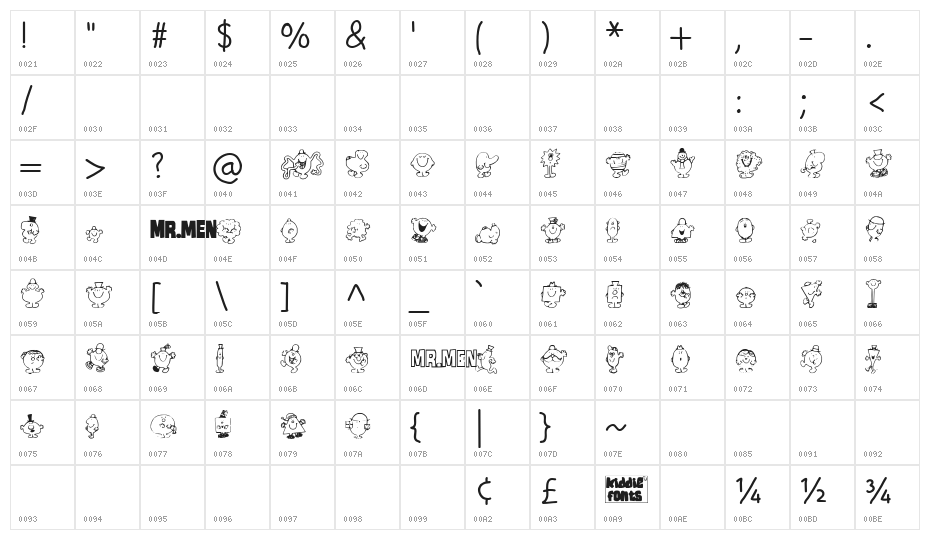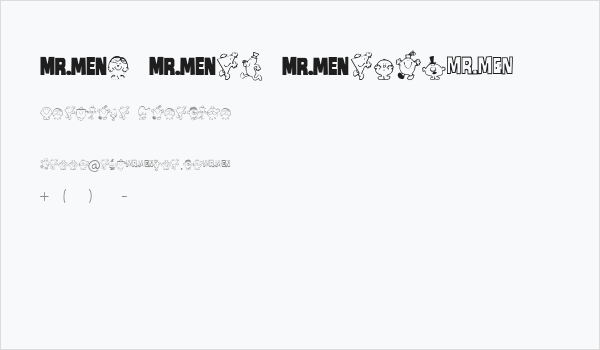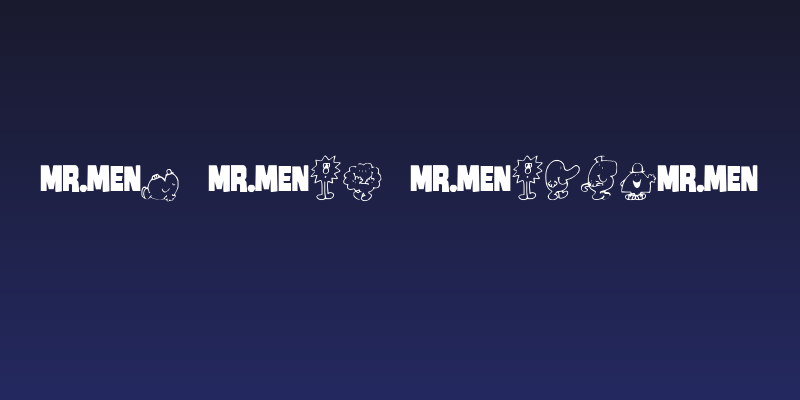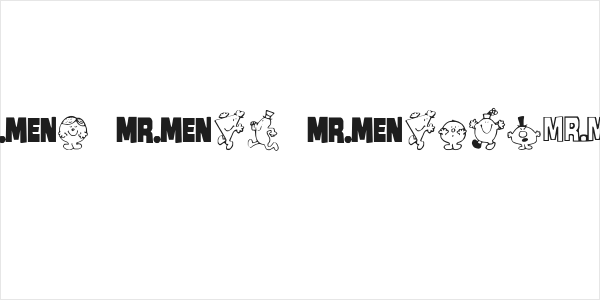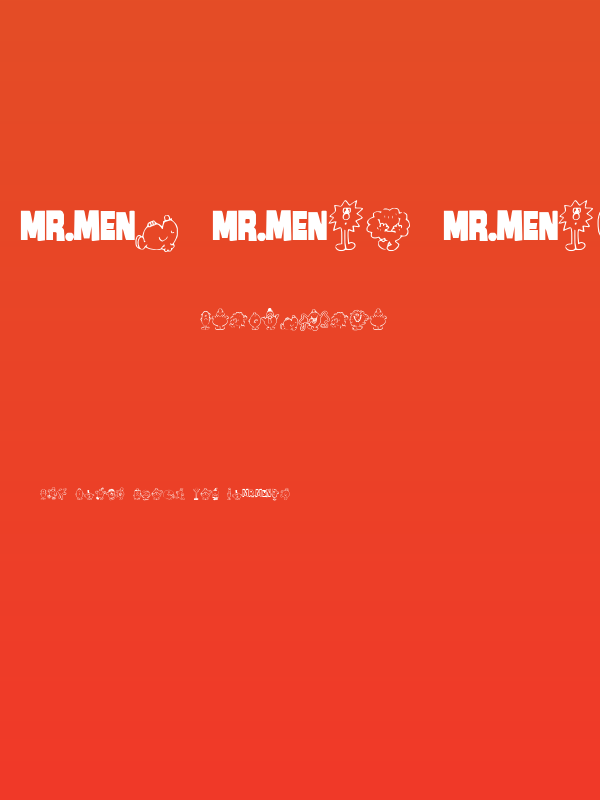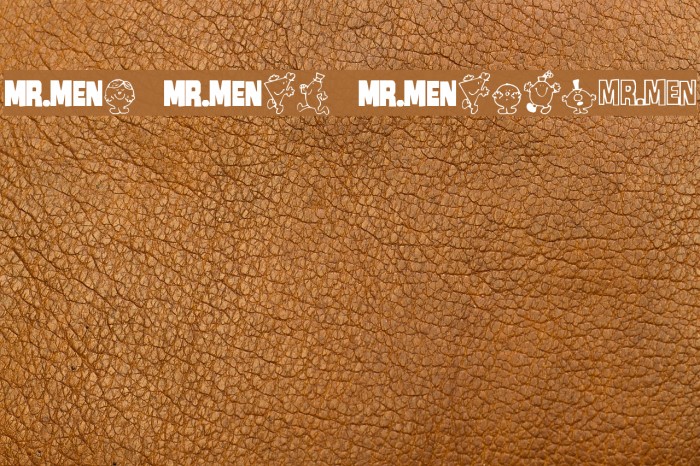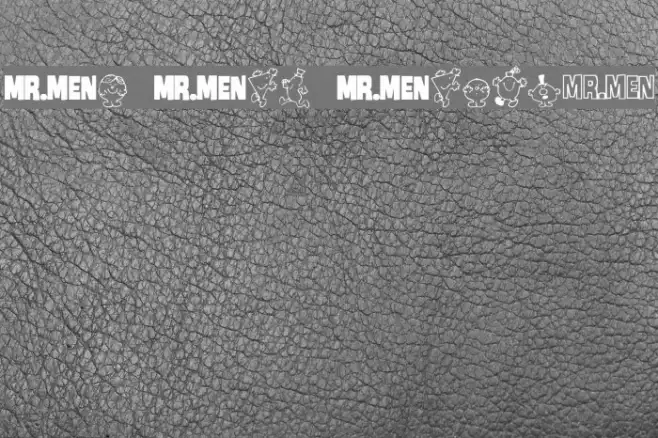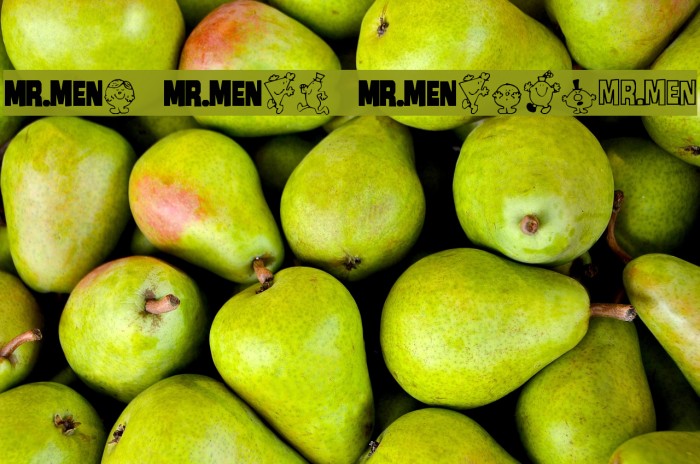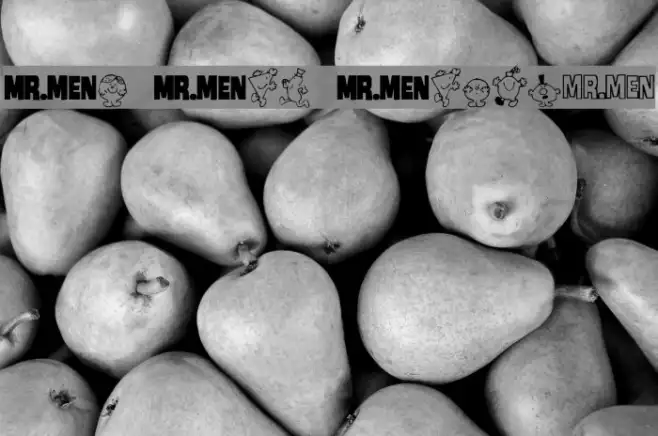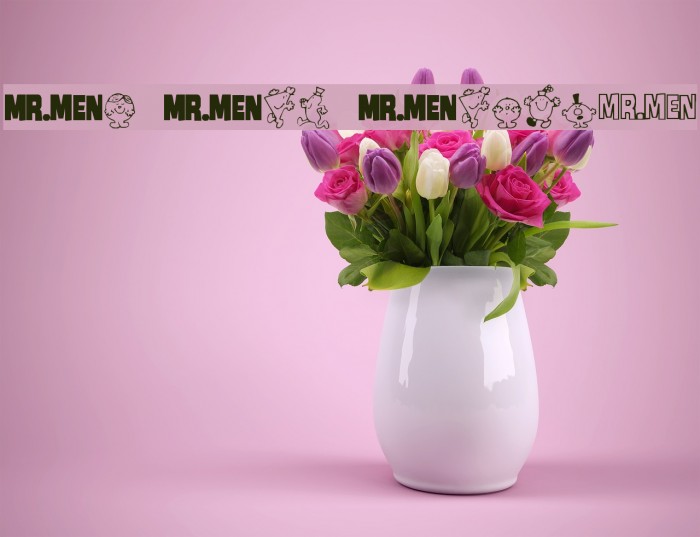
Mr Men Medium Font
| Stile generale | Playful, Cartoonish |
| Caso d'uso | Headlines, Logos, Decorative text |
| Progetti proposti | Ideal for children's books, playful posters, educational materials, and themed party invitations. |